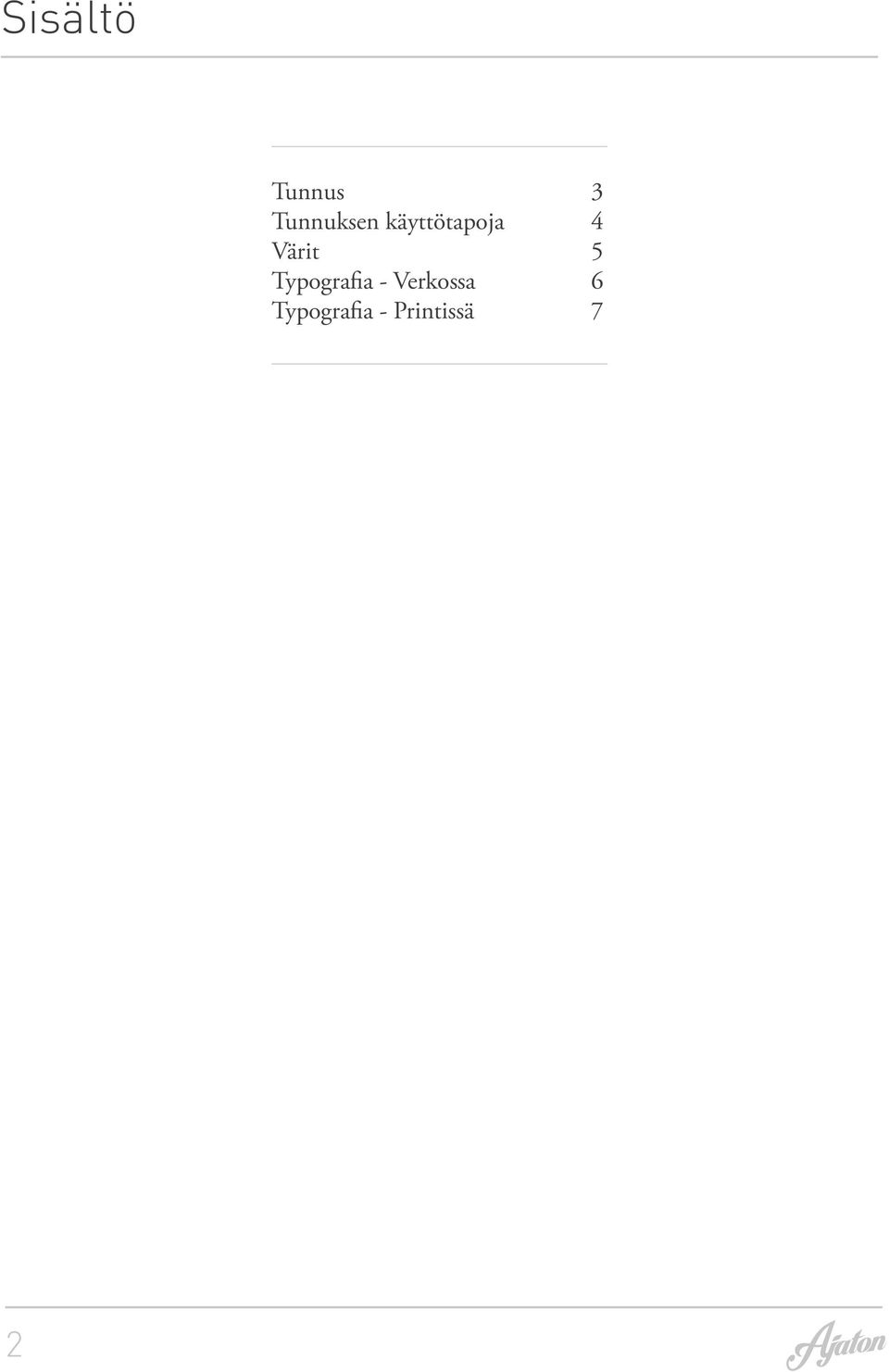
6 Typografia - Verkossa MINUN MAISEMANI - MAALLA JA KAUPUNGISSA Esimerkki sloganista - Lato - Black / Lato - Light ALAOTSIKKO VÄRJÄTTYNÄ Lorem ipsum dolor sit amet, consectetuer adipiscing elit. Sed posuere interdum sem. Quisque ligula eros ullamcorper quis, lacinia quis facilisis sed sapien. Mauris varius diam vitae arcu. Sed arcu lectus auctor vitae, consectetuer et venenatis eget velit. Sed augue orci, lacinia eu tincidunt et eleifend nec lacus. Donec ultricies nisl ut felis, suspendisse potenti. Lorem ipsum ligula ut hendrerit mollis, ipsum erat vehicula risus, eu suscipit sem libero nec erat. Aliquam erat volutpat. Sed congue augue vitae neque. Nulla consectetuer porttitor pede. Fusce purus morbi tortor magna condimentum vel, placerat id blandit sit amet tortor. Mauris sed libero. Suspendisse facilisis nulla in lacinia laoreet, lorem velit accumsan velit vel mattis libero nisl et sem. Proin interdum maecenas massa turpis sagittis in, interdum non lobortis vitae massa. Lato - Fonttiperhe Lato fonttiperhe on yksi googlen omistamista fonteista. Sen pyöreät, linjakkaat ja modernit muodot soveltuvat erinomaisesti Vihervuoden käyttötarkoituksiin. Otsikoissa ja ja leipäteksteissä käytetään pääsääntöisesti Lato-light-fonttia. Ingressiteksteissä voidaan käyttää Lato-regular-fonttia ja boldatessa Lato-bold-fonttia. Korostaessa otsikoita voidaan käyttää myös Lato-Black-fonttia. Kaikki Lato fontit Lato Hairline Lato Light Lato Regular Lato Bold Lato Black Sekä italic versiot Leipäteksti - Lato - Light 6
7 TYPOGRAFIA Typografia - Printissä OTSIKOT JA VÄLIOTSIKOT DIN DIN LIGHT REGULAR MEDIUM LEIPÄTEKSTI JA INGRESSI ADOBE GARAMOND ADOBE GARAMOND REGULAR SEMIBOLD 7 15